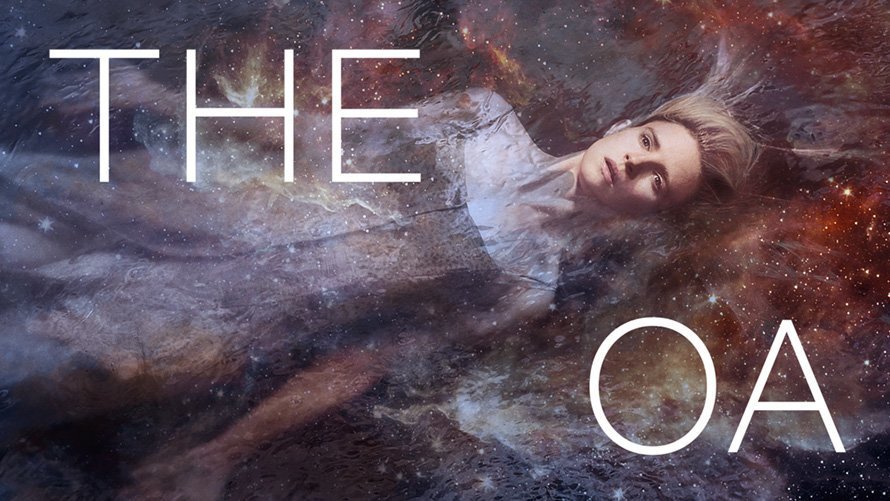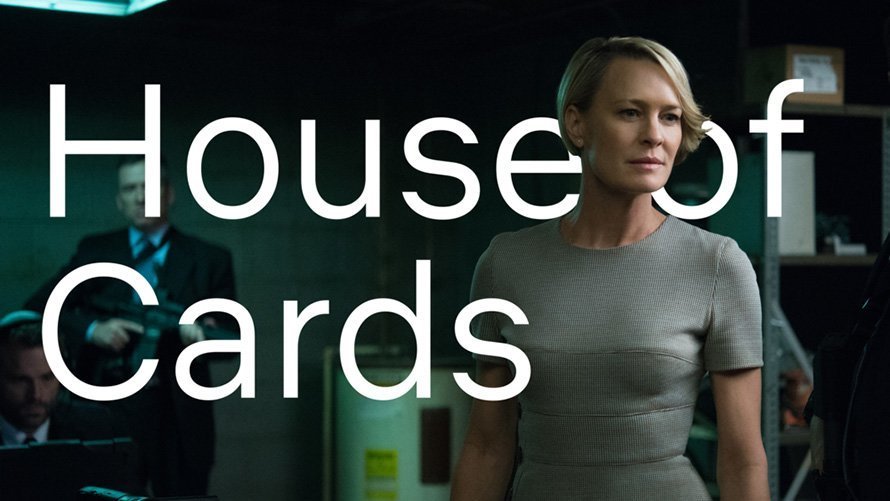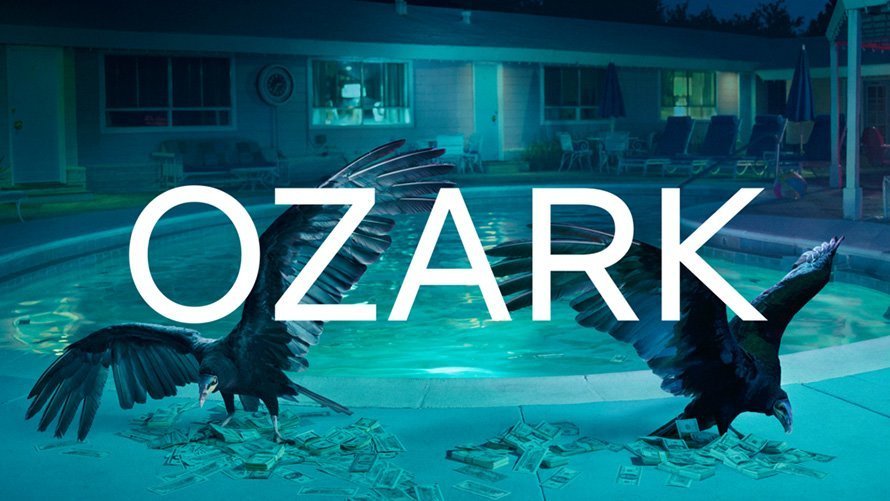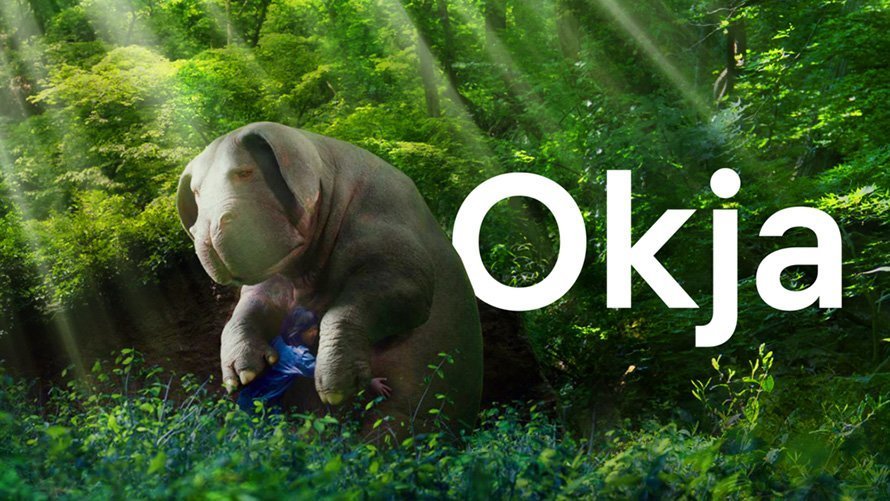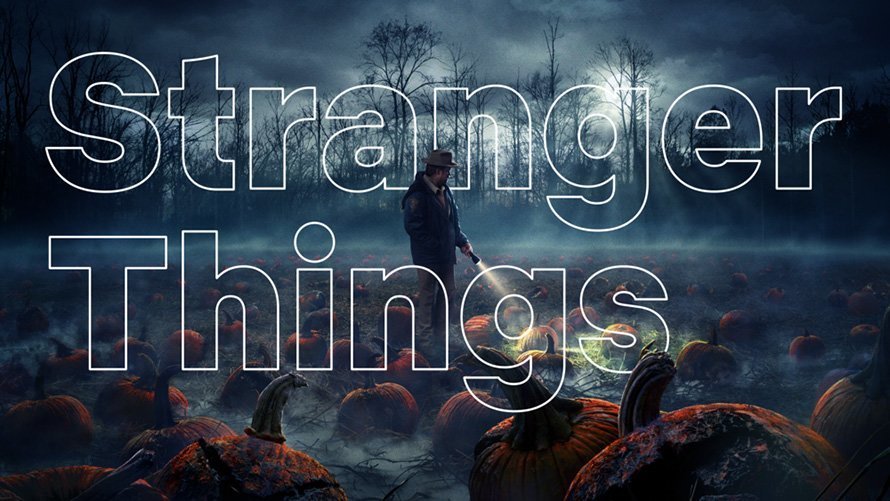
Netflix sadece orijinal içerikler üreten bir kurum değil. Kullanıcı arayüzü ve kullanıcı deneyimini önemseyen de bir yer. Kullanıcı alışkanlarını ölçüyor ve adapte olabiliyor, hatta thumbnail görselleri kişisel zevklere göre değişebiliyor. Hayatımıza “Netflix and chill” söylemini getirdiler. Bu söylem aynı zamanda Netflix’in başarısını da özetliyor çünkü Netflix 190’dan fazla ülkede 109 milyonun üzerinde üyeye sahip. Netflix yılllar içerisinde logosunu evirdi, kullanıcı arayüzünü çevirdi derken şimdi de Noah Nathan ve Tanya Kumar’ın yönettiği marka tasarım ekibi yeni sans-serif “Netflix Sans” font ailesini tasarladı.
Font lisanslama Amerika’da markalara pahalıya patlayabiliyor. Bu yüzden Apple, Samsung, Google, Microsoft gibi markalar kendi yazı tiplerini tasarlıyorlar ve marka kimliklerini de sağlamlaştırmış oluyorlar. Bu sefer sadece kendi iç marka takımlarıyla çalışmadılar, yazı karakterlerinin tasarım sürecine Dalton Maag de dahil oldu.
Göz Yormayan Sans Serif
Yeni sans-serif, eğlence endüstrisinde her yerde görebileceğiniz yazı karakteri olan Gotham‘ın yerini aldı. Netflix’in tasarımcıları, markanın kendi adını verebileceği bir yazı karakterine sahip olmasının ona her yıl milyonlarca dolar tasarruf edeceğini söylüyor.
Temiz, okunaklı ve nötr olan yazı tipi kullanıcının içeriğe, kullanılan cihazdan bağımsız olarak odaklanmasını hedefliyor. Font ailesi dikkat dağıtmamak adına minimal bir estetiğe sahip. Harf biçimleri ekran estetiğini ve yararcı fonksiyonları taşıyor. Üst açılarda sinematik tasarımın izlerini, alt açılarda da daha kompakt ve geometrik izleri taşıyor.
Mesela t harfinin tepesindeki kemerli kesim, markanın sembol ve sembolüne çok benzeyen sinematik eğriyi görebilirsiniz. Tasarım ekibi logoyu oluştururken de 50’li ve 60’lı yıllarda geniş ekranlı film çekimlerinde kullanılan anamorfik lensli CinemaScope’un logosundan da ilham almıştı.
Netflix Sans font ailesi regular, light, thin, medium, bold ve black olmak üzere temel bir font ailesinin sahip olması gereken bütün bireylere sahip. Genel olarak harf ailesine bakarsak ekranda gözü yormayacak şekilde. Helvetica gibi üzerine belgeseller yapılacak bir font değil ya da Futura gibi “bugünün ve geleceğin fontu” diye de çıkmıyor. Ama Netflix kullanıcı dostu olmaya özen gösteriyor ve font ailesi yeterince “chill”.
Netflix Sans Thin:
Netflix Sans Light:
Netflix Sans Regular:
Netflix Sans Medium:
Netflix Sans Bold:
Netflix Sans Black: